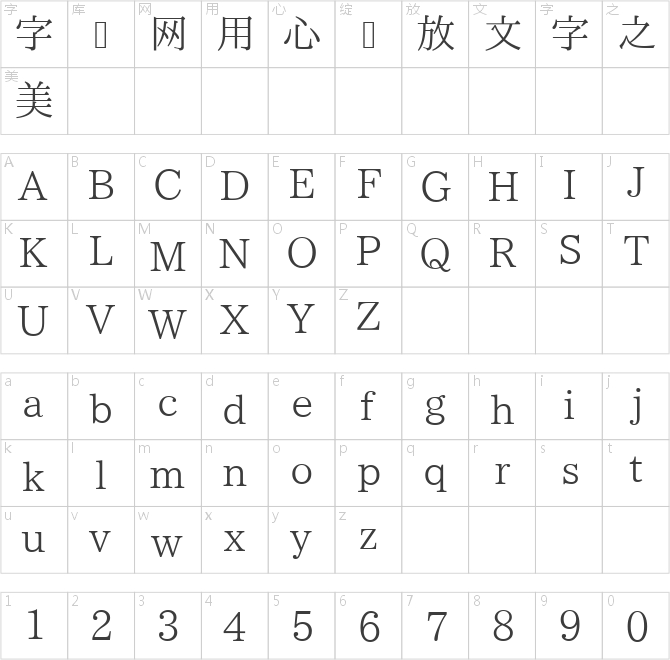
字体名称: 紫阳花明朝Z
紫阳花明朝Z
紫阳花明朝Z介绍
紫阳花明朝Z字体下载AjisaiMinchoZ
紫阳花明朝Z是一款充满古典味道的免费商用宋体字形,紫阳花,又名八仙花、紫阳花、七变化、粉团花,原产于中国四川一带及日本。相对于中国,紫阳花在日本更家喻户晓,日本很多人都喜爱紫阳花,不少地方有紫阳花的种植园。诗人白乐天曾到某寺庙中,住持曾以该寺不知名的花朵询问他,而他命名此花为”紫阳”。后来这名称传至日本,所以日本就称此花为紫阳花。
这款字体以紫阳花命名,能让人深深地感受到这款字体的优雅之处,特别适合古典风格的海报设计。在日本,一般会把宋体字形称为明朝体。由于紫阳花明朝Z是由日本的设计师制作,所以字符是以JIS水准为标准,对简体的支持比较差,但是对繁体支持很好。